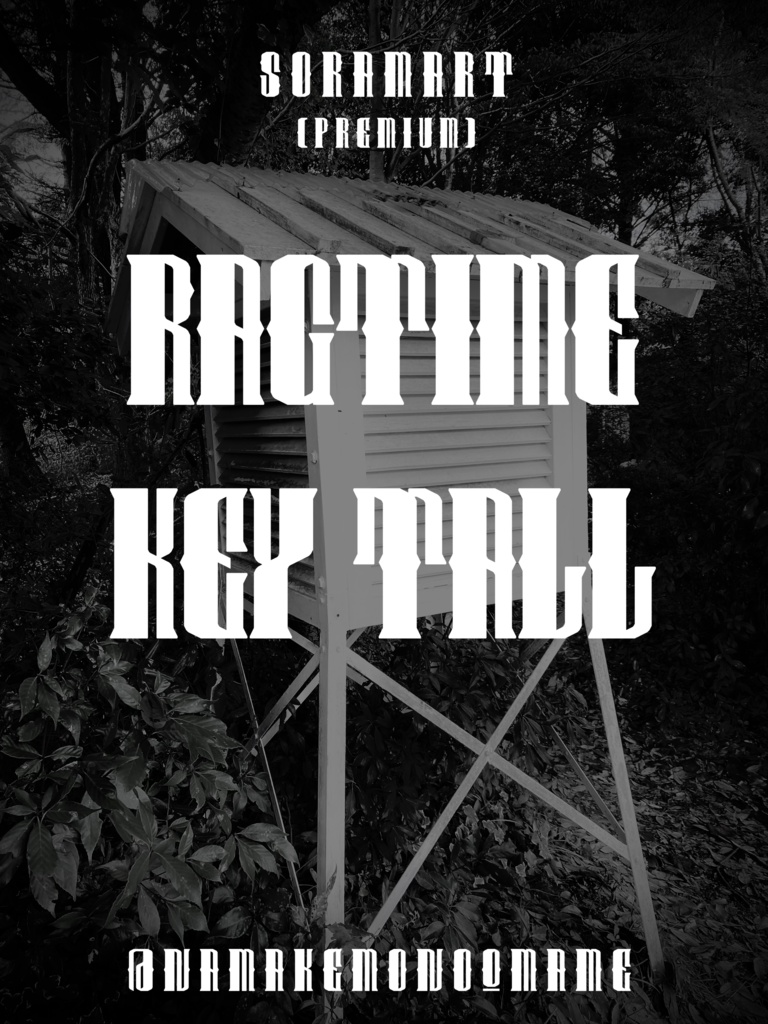
そらマートフォントデータ”Ragtime Key Tall”Digital2,500 JPYAdd to CartBuy a GiftAbout Giftクラシカルでソリッドだけど、文字を並べると”ゆらぎ”や”リズム感”が見えてくるフォントの縦長版 "Ragtime Key Tall" です。 「TrueTypeフォントファイル」という形式です。 ダウンロードした後、Zipファイル内のデータをインストールしてお使いください。 このフォントは商用利用可となっております。 お客様の制作・創作活動のお役に立てれば幸いです。 ※使用上の注意事項などは、添付のReadmeをお読みください。 ※このフォントは、有料販売専用商品です。そらマートVisit FANBOX!Fontsフォントデータ”RANMMA Drive”そらマート0 JPYFontsフォントデータ”Dandy Laser Max”そらマート2,500 JPYFontsフォントデータ”Dandy Laser”そらマート2,500 JPYFontsフォントデータ”Bubblegum Beat”そらマート2,500 JPYFontsフォントデータ”Caltrop Serif LLL”そらマート2,500 JPYFontsフォントデータ”Caltrop Serif LL”そらマート2,500 JPYFontsフォントデータ”Caltrop Serif”そらマート2,500 JPYFontsフォントデータ”Tonik Crate Super Long”そらマート2,500 JPYFontsフォントデータ”Dot Eat Bug Acid”そらマート2,500 JPYFontsフォントデータ”Dot Eat Bug Mild”そらマート2,500 JPYFontsフォントデータ”Dot Eat Bug”そらマート2,500 JPYFontsフォントデータ”Solid Voltage Strike”そらマート2,500 JPYFontsフォントデータ”Solid Voltage”そらマート2,500 JPYFontsフォントデータ”Henge Edge Rock”そらマート2,500 JPYFontsフォントデータ”Henge Edge Tall”そらマート0 JPYFontsフォントデータ”Henge Edge”そらマート0 JPYFontsフォントデータ”Chisel Stroke Wide”そらマート2,500 JPYFontsフォントデータ”Chisel Stroke”そらマート2,500 JPYFontsフォントデータ”Crushed Can Serif Empty”そらマート2,500 JPYFontsフォントデータ”Crushed Can Serif Wide”そらマート2,500 JPYSee More